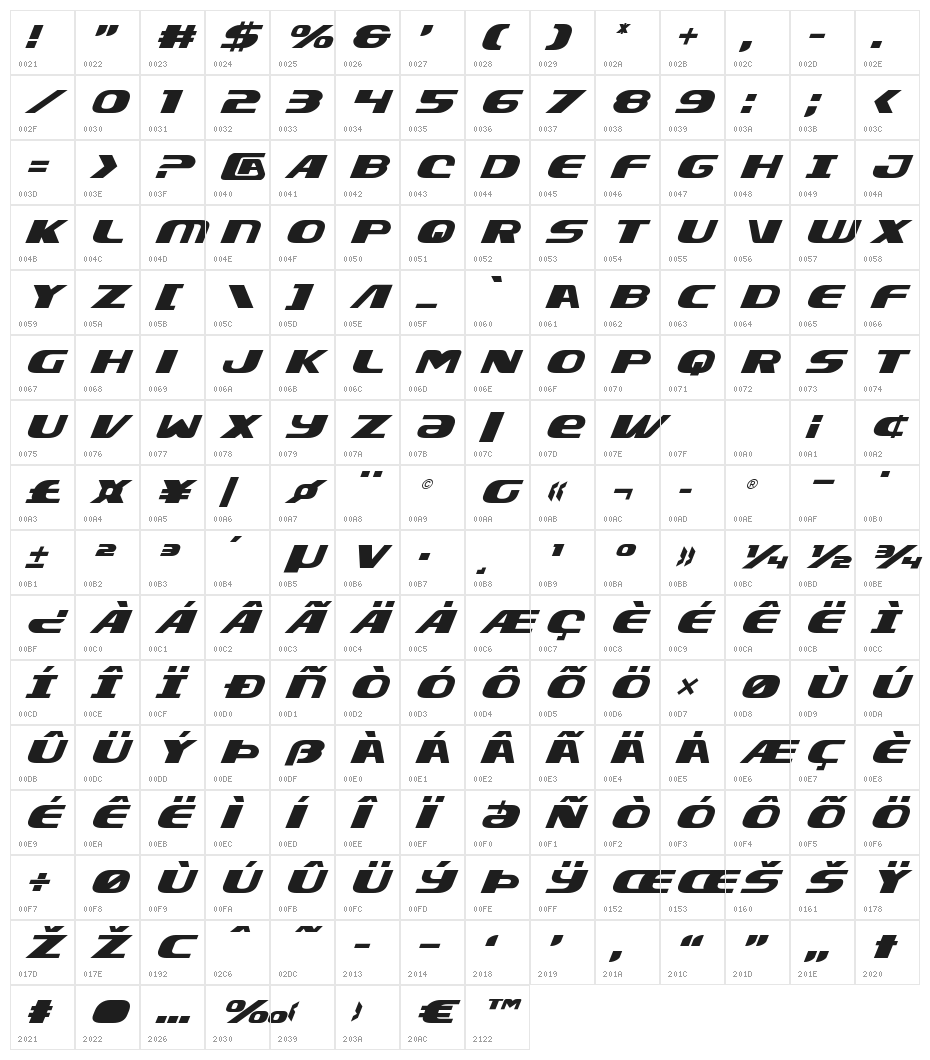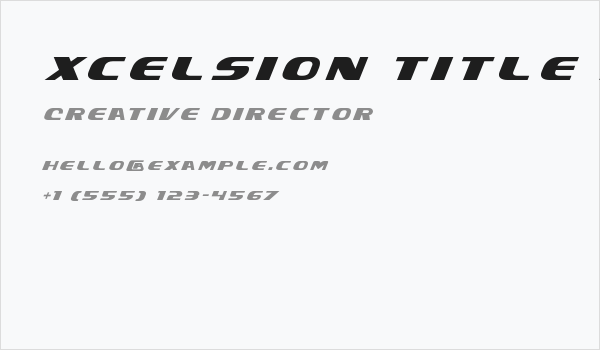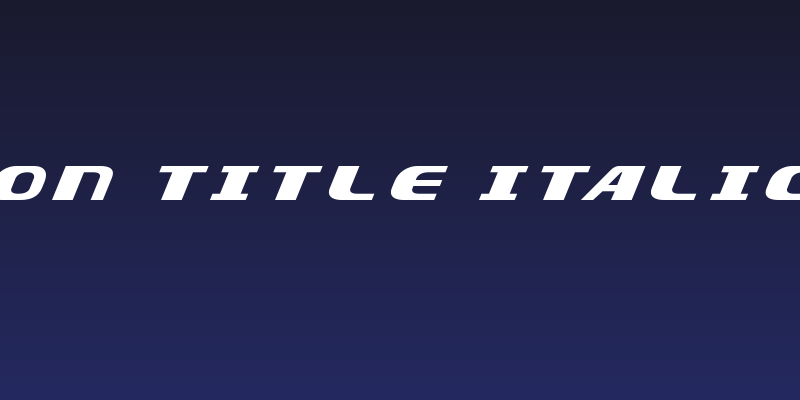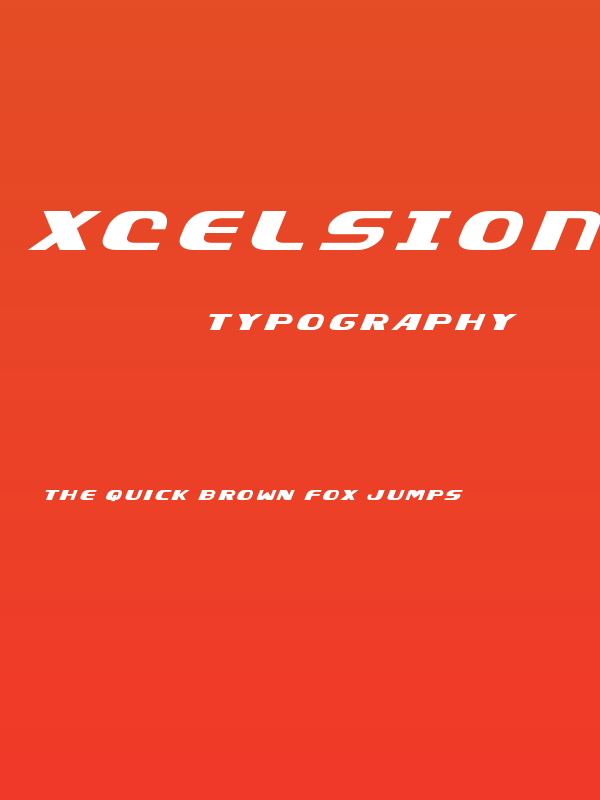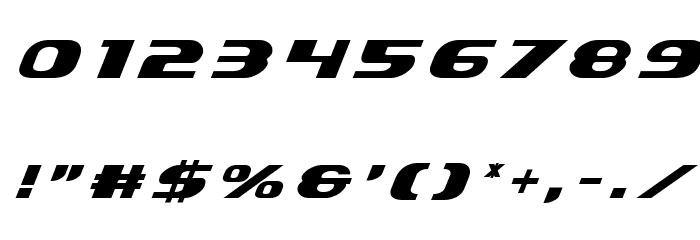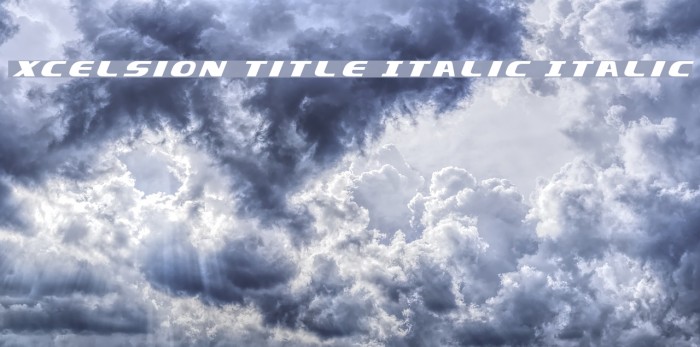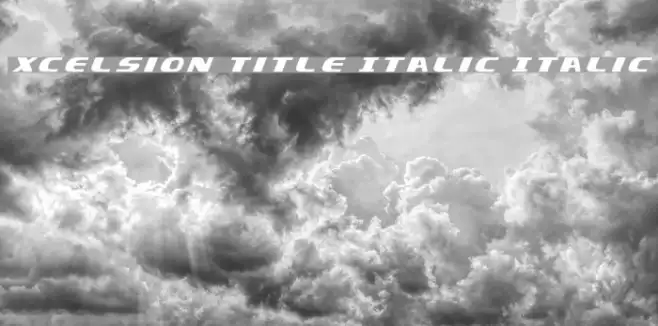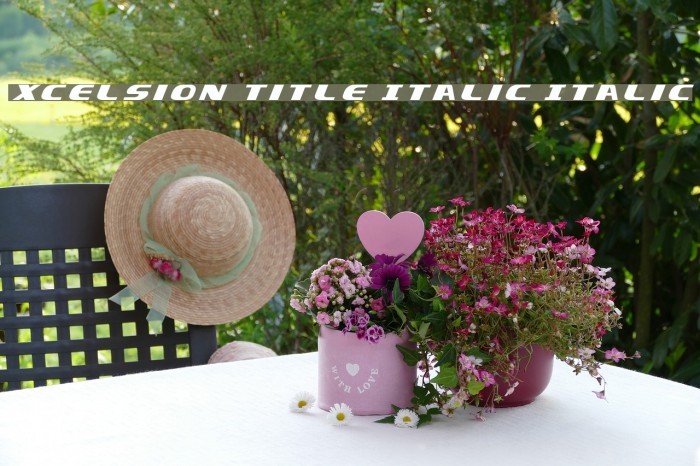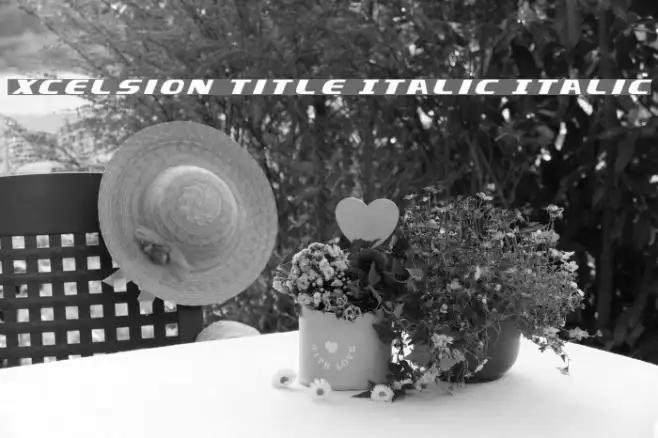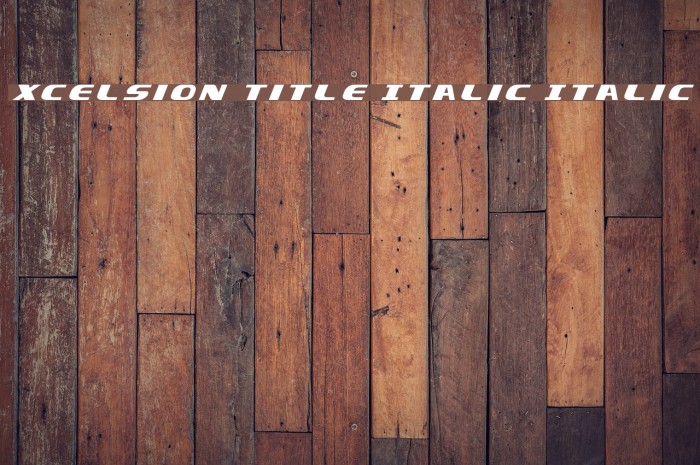
Xcelsion Title Italic Italic Font
✎ Thick
| Vorgeschlagene Projekte | Ideal for sports branding, automotive designs, dynamic posters, and modern advertising campaigns. |